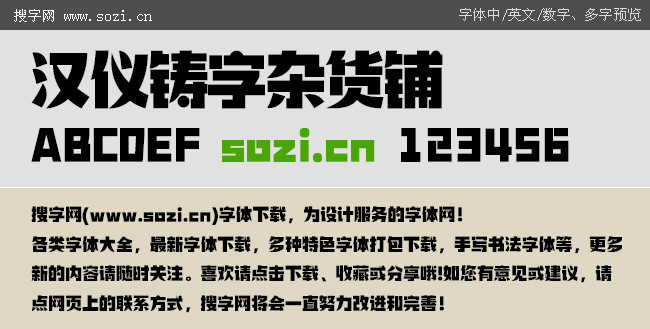
漢儀鑄字雜貨鋪
搜字網(wǎng)給大家提供一款漢儀鑄字雜貨鋪中文字體下載,漢儀鑄字雜貨鋪字體是一款充滿趣味的藝術(shù)字體,筆畫處理突破常規(guī),靈活多變,厚重的字形中凸顯了幾分俏皮,既穩(wěn)重又有趣味,適用于畫冊設(shè)計、海報設(shè)計、包裝設(shè)計等場合使用。(本字體為個人非商用版,如需要商用請聯(lián)系漢儀公司購買版權(quán))